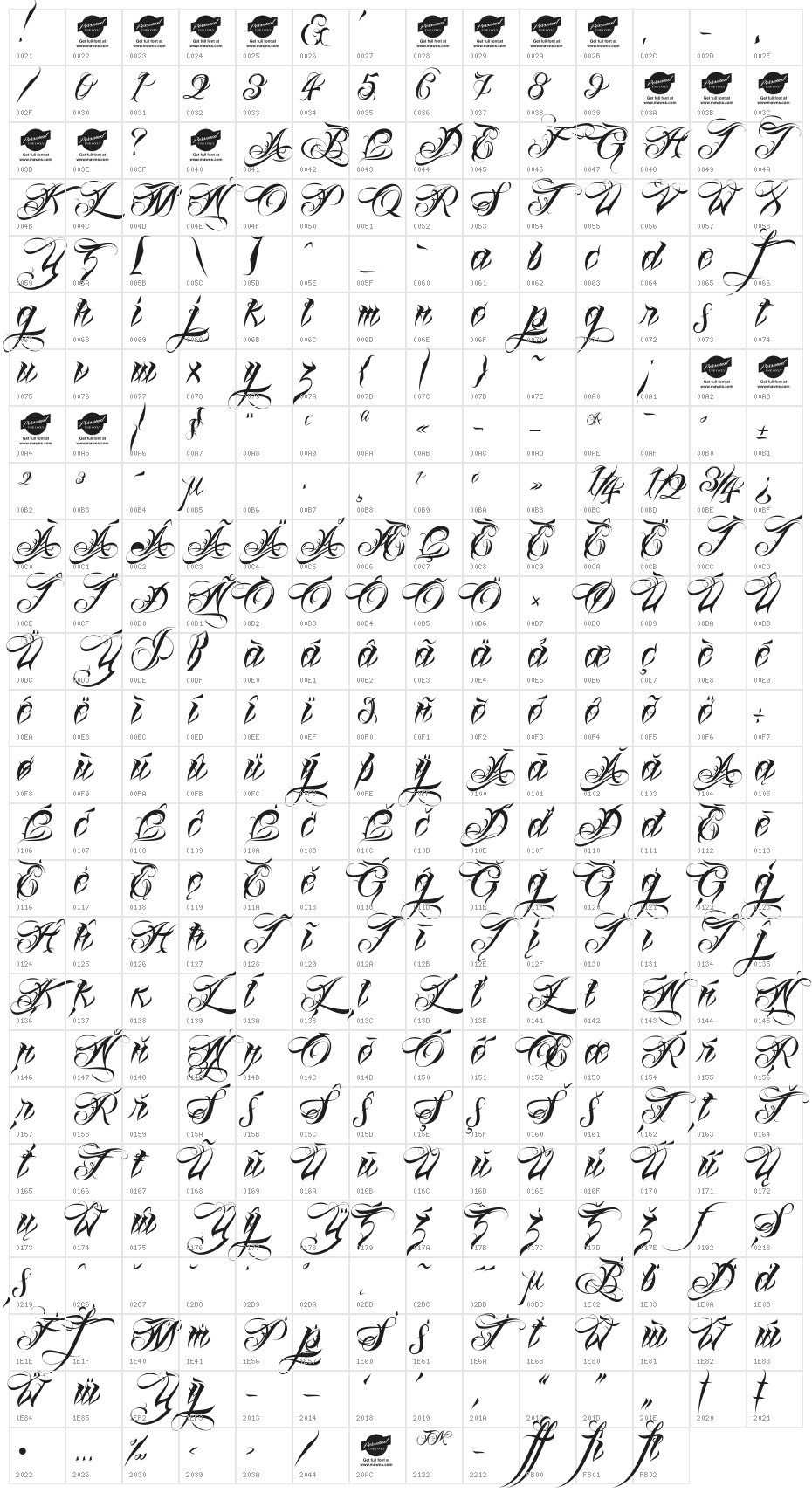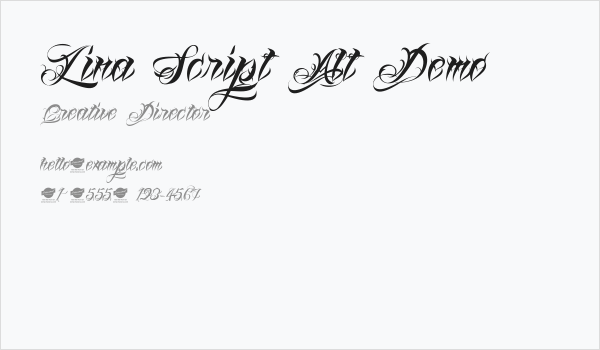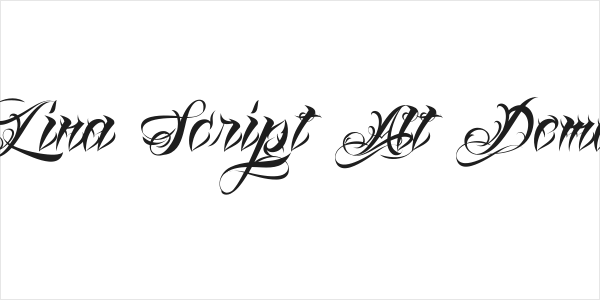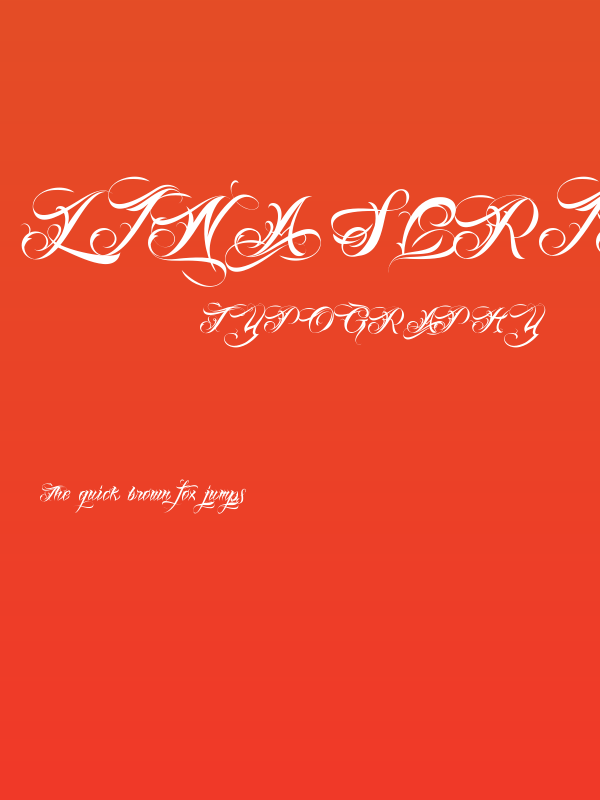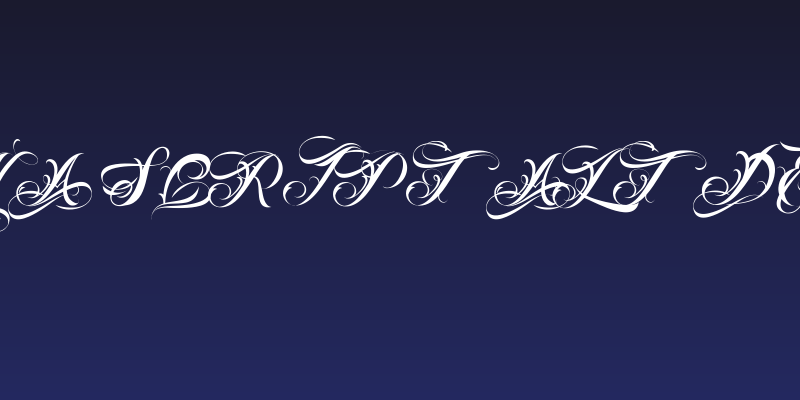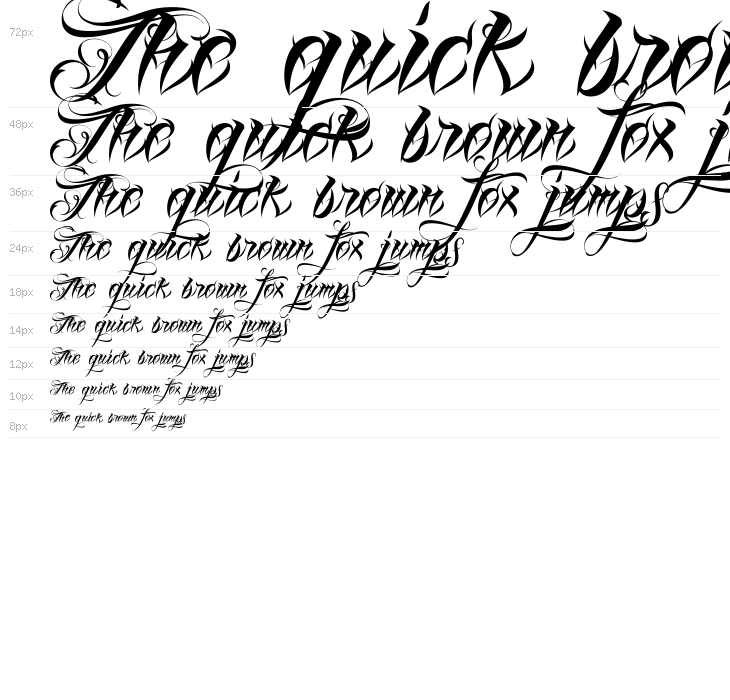
Lina Script Alt Demo Font
| Anwendungsfall | Logos, Invitations, Artistic projects |
| Vorgeschlagene Projekte | Ideal for wedding invitations, luxury branding, artistic posters, and elegant stationery. |